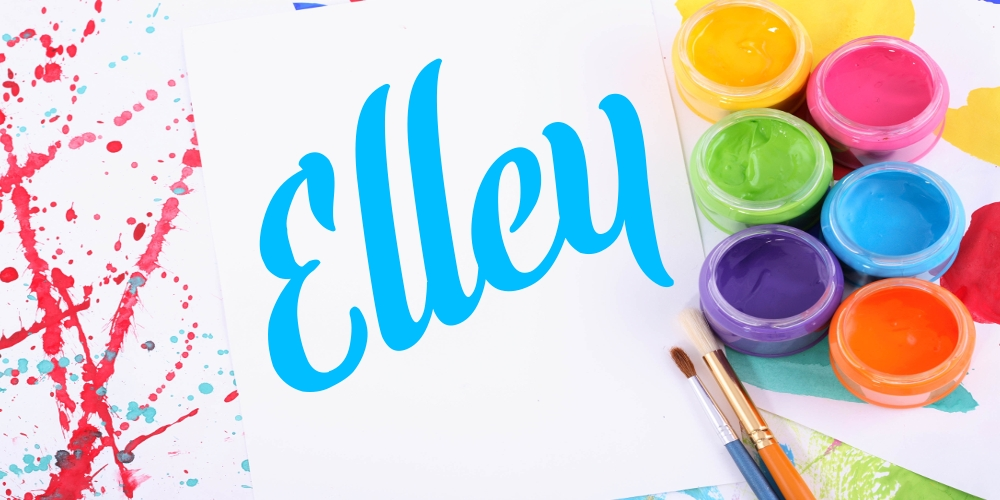
A fonte Elley é uma escolha perfeita para quem busca um estilo elegante e suave em seus projetos digitais. Desenvolvida pelo designer Hamilton, esta fonte script se destaca com suas curvas fluidas e traços delicados que criam um ar de sofisticação. Ideal tanto para assinaturas de emails quanto para criações gráficas como logotipos ou editoriais do blog, Elley oferece uma linguagem suave e envolvente. Seu formato levemente curvilíneo traz um toque único que torna qualquer projeto em que seja aplicada instantaneamente especial. Se você está procurando por um estilo de font que se destaque sem ser brusco ou formal, a Elley é uma ótima opção para sua lista de recursos gráficos.